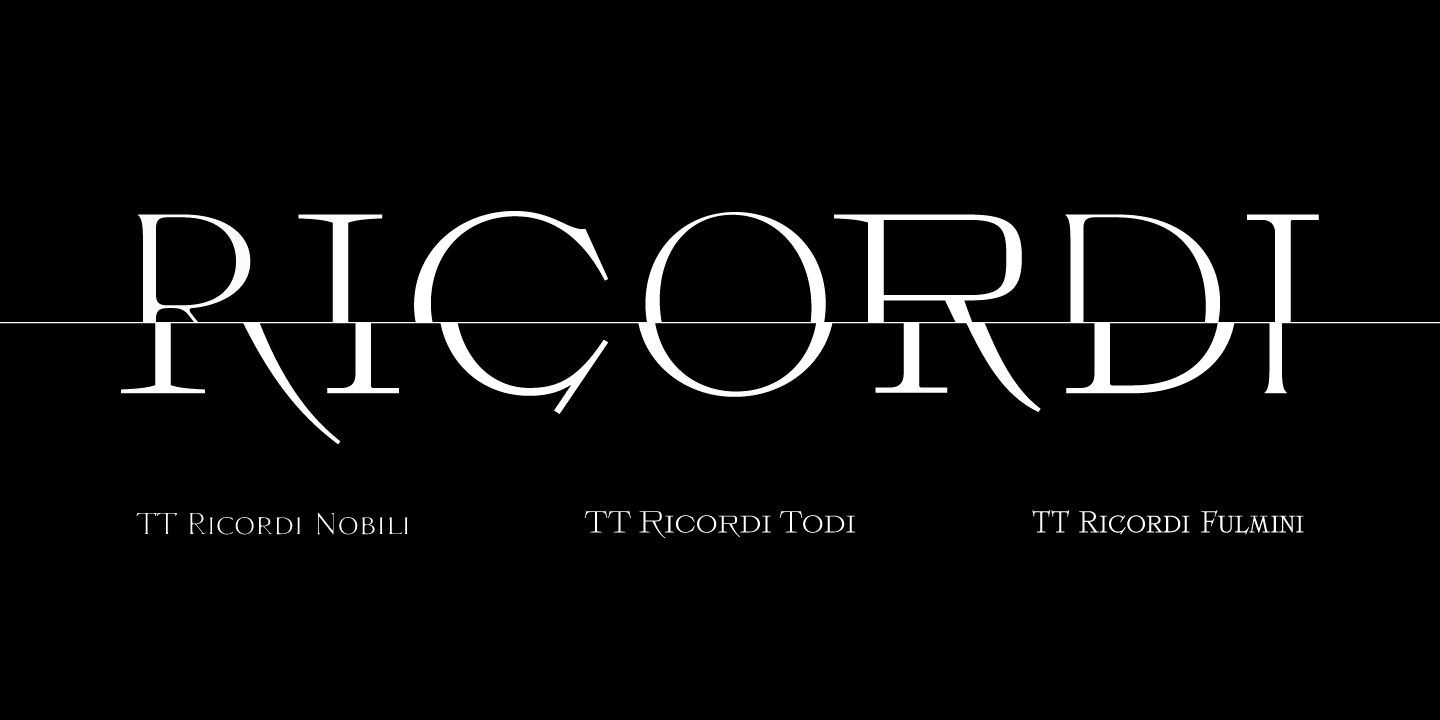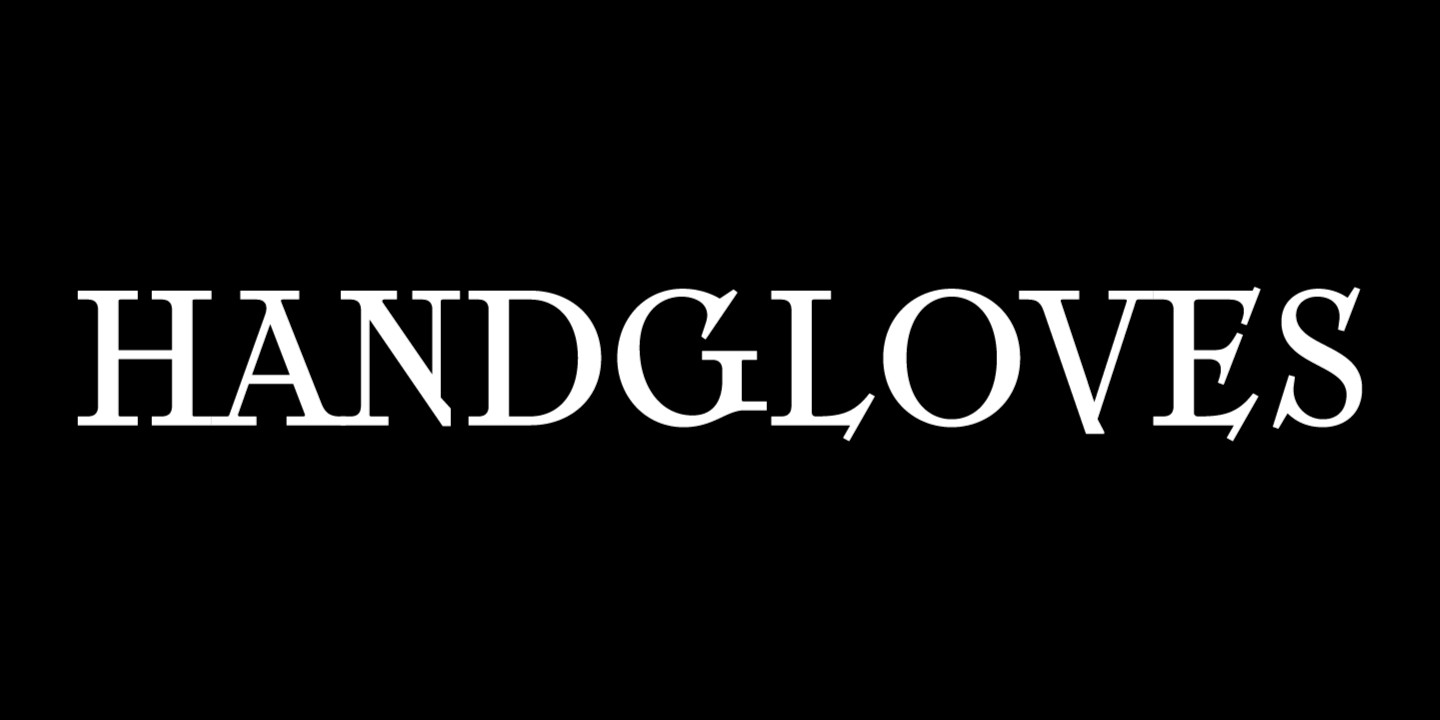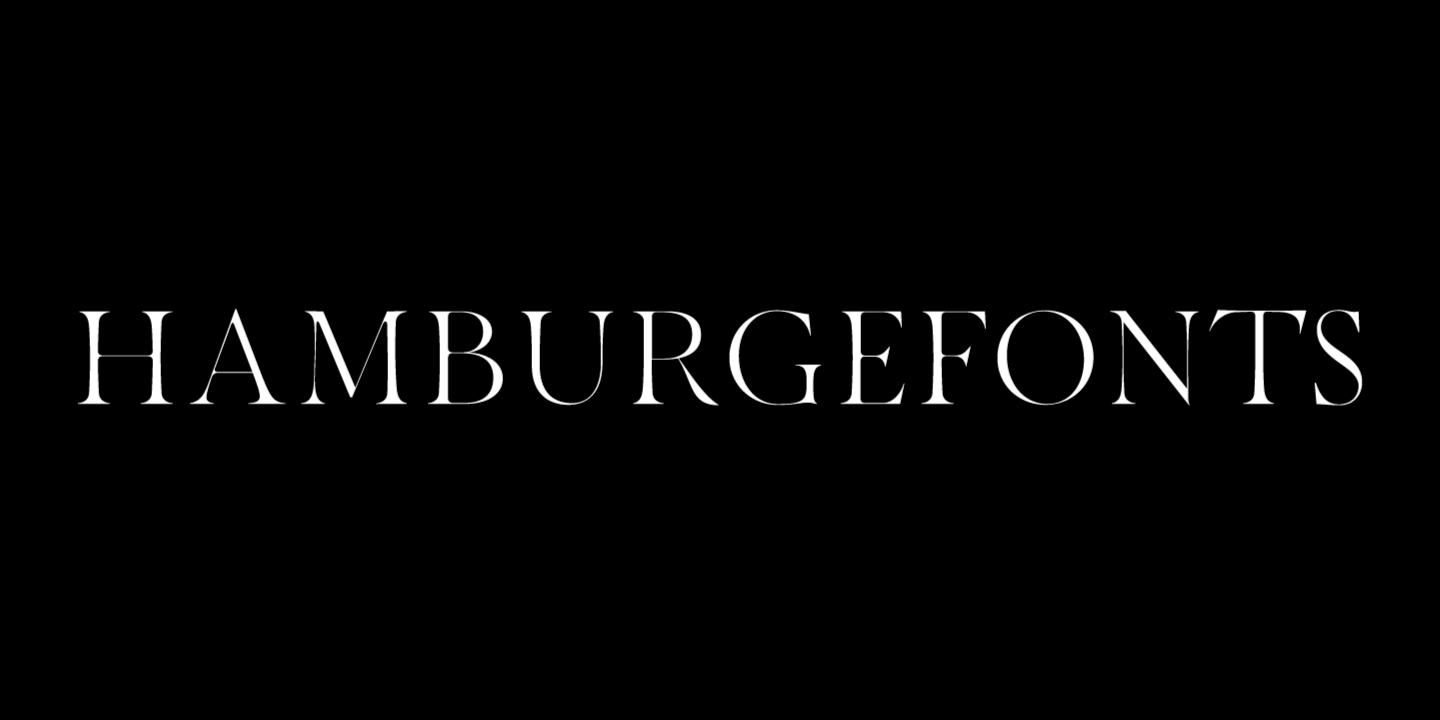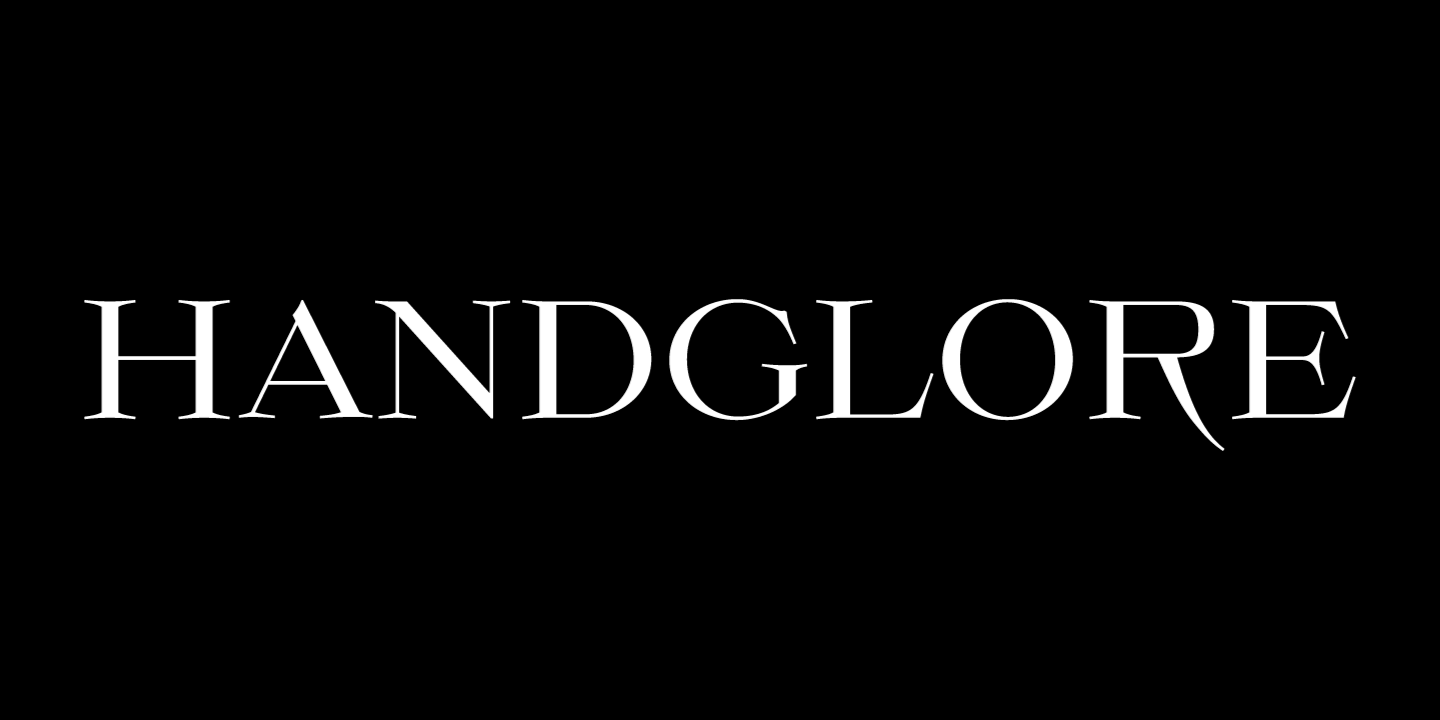
История создания шрифтовой гарнитуры TT Ricordi
Гарнитура TT Ricordi — это коллекция из трёх акцидентных заголовочных антикв, призванных значительно разнообразить традиционную шрифтовую палитру. При этом все три шрифта близки по толщине и схожи своими кассовыми составами, представлены в прописном и капительном наборе, который заменяет собой строчные знаки. В шрифтах есть широкая поддержка латинских языков и поддержка базовой кириллицы.
Семейство шрифтов Ricordi
Как возникла эта идея
Каждый шрифт из гарнитуры TT Ricordi рисовался отдельным дизайнером и за каждым шрифтом лежит своя история.
TT Ricordi Todi
«Исторические источники — это прекрасная отправная точка для работы над шрифтом. Несмотря на то, что формы уже определены оригиналом, проект все равно может пойти в абсолютно разных направлениях. Можно сделать шрифт, который бережно сохранит все исторические артефакты, а можно преобразовать оригинал в нечто ультрасовременное.
За все мои поездки в Италию у меня накопилось довольно много фотографий исторических надписей, и каждый раз, когда я их пересматриваю, руки тянутся что-то из них сделать. Когда мы решились воспользоваться ими в нашей работе, у нас еще не было уверенности, насколько эта концепция будет востребована.
Подумав над тем, как и где могли бы использоваться подобные шрифты, мы пришли к выводу, что они должны быть скорее концептуальными и акцидентными, чем функциональными. Поэтому намного интереснее было бы поработать над несколькими разными концепциями, чем развивать одну в сторону увеличения семейства. А если мы говорим про несколько разных концепций, было логично дать их разным дизайнерам. Таким образом мы могли работать над ними параллельно, обсуждать вместе проекты друг друга, делиться опытом, заимствовать наработки, но при этом все равно характер шрифтов получился абсолютно разный.»
Юлия Гонина, Арт директор
TT Ricordi Todi является широкой антиквой с классической основой и современным характером. Шрифт получился утонченным, но при этом острым, а местами даже напористым и агрессивным. Шрифт нарисован Юлией, а референсом для проекта послужили таблички с выгравированными названиями улиц из небольшого итальянского городка Тоди. Основным вызовом было распознать характерные особенности у знаков и подчеркнуть их на современный манер. Кроме того, нужно было нарисовать такую кириллицу, которая бы не уступала латинице по своей выразительности.
Эволюция Ricordi Todi
У шрифта TT Ricordi Todi достаточно широкие пропорции знаков, а контраст в пропорциях практически отсутствует. Основной особенностью шрифта является сочетание плавных круглых форм с нарочито сквадраченными формами. Кроме того, шрифту свойственны четкие и острые детали у знаков, преувеличенные выносные элементы и приглушенный контраст. Из интересного: в шрифте можно выбирать между характерными длинными выносными элементами и более спокойной версией, можно найти стилистический сет с треугольными точками, альтернативные версии знаков EF и две формы для буквы Ф — круглую и сквадраченную.
TT Ricordi Nobili
«Моя работа над TT Ricordi, конечно, отличалась от привычной работы над нашими шрифтами, такими как TT Norms, например. Этот проект был для меня в первую очередь про творчество, выразительность форм и акциденцию. Здесь мне была предоставлена максимальная свобода в поиске форм, что было и большим удовольствием, но также и большим вызовом. Я очень довольна самим процессом работы: погружением в формы антиквы, римского капитального, а затем отсечением всего лишнего от шрифта, чтобы он стал тем, чем он стал. Я, определенно, не первый дизайнер на планете, кто пытается сделать современный шрифт на основе традиционных форм, но я считаю, что каждый подобный проект глубоко индивидуален и этим ценен.  Отдельная гордость проекта — дискретные лигатуры, в них максимальная концентрация характера этого шрифта.»
Анна Тихонова, шрифтовой дизайнер
Эволюция Ricordi Nobili
TT Ricordi Nobili является акцидентной антиквой с богатой римской родословной и современными взглядами на мир. Из толпы выделяется своей тонкостью и изящностью.
Шрифт нарисован Аней, а вдохновением для него послужила надпись, высеченная на каменном полу собора во Флоренции. Из-за того, что по надписи ходили люди, часть букв со временем истончилась и стерлась. Это ощущение пропадающих или мерцающих элементов хотелось уловить и внедрить в проект.
У шрифта TT Ricordi Nobili высокий контраст, при том, что сам шрифт достаточно тонкий. Засечки в шрифте совсем не массивные, но при этом акцидентные. В шрифте ощущается некое напряжение, и это напряжение считывает зритель. Можно сказать, что за внешним классическим фасадом кроется довольно современный сюжет. В шрифте есть большой набор дискретных лигатур, которые позволяют создавать интересные сочетания и расширять возможности шрифта.
TT Ricordi Fulmini
«Для меня проект стал необычным уже на стадии ТЗ. На скетчи, отрисовку и тестирование у нас был месяц. Это бодрило и не давало впадать в созерцание. Самым сложным для меня оказалось уйти от старостильности и придать шрифту современное звучание. Для этого пришлось отказаться от полноты референса и сделать шрифт более тонким и четким.»
Марина Ходак, старший шрифтовой дизайнер
Эволюция Ricordi Fulmini
TT Ricordi Fulmini является модной современной антиквой, крепко держащейся за исторические корни. Шрифт получился похожим на цветок чертополоха: яркий и цепляющий, но всё ещё утонченный и нежный. TT Ricordi Fulmini нарисован Мариной, а первоначальным вдохновением для проекта послужила надпись на алтаре из национальной галереи Умбрии в Перуджи. В процессе вытягивания «в современность» шрифт полностью преобразился и раскрылся с новой стороны.